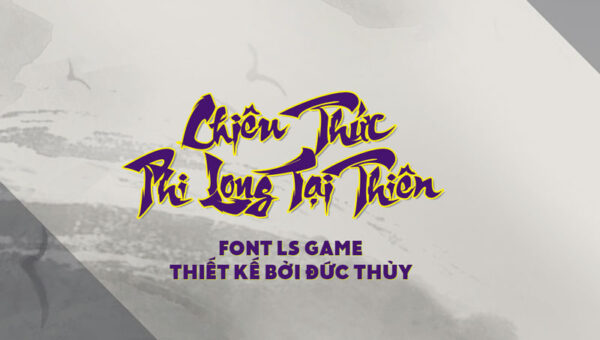
Font kiếm hiệp LS Game
Bộ font kiếm hiệp Ls Game phù hợp thiết kế content game thể loại game và các ấn phẩm bìa sách, quảng cáo, baner game…
• Font game kiếm hiệp này được thiết kế bởi Đức Thủy, Font lấy cảm hứng kho chơi game Võ lâm truyền kỳ.
• Font đặc biệt có nhiều ký tự thay thế khác nhau và được tối ưu để phù hợp trong nhiều trường hợp thiết kế.
• Các ký tự được thêm quy tắc gõ, hoặc insert vào table glyphs của từng chữ cái.
Bộ font kiếm hiệp Ls Game V1 phù hợp thiết kế content game thể loại game và các ấn phẩm bìa sách, quảng cáo, baner game…
Bộ font game kiếm hiệp này được thiết kế bởi Đức Thủy, Font lấy cảm hứng kho chơi game Võ lâm truyền kỳ.
Admin muốn tạo nên sự khác biệt trong các sản phẩm game, tăng giá trị cho việc PR game mới.
Font đặc biệt có nhiều ký tự thay thế khác nhau và được tối ưu để phù hợp trong nhiều trường hợp thiết kế.
Các ký tự được thêm quy tắc gõ, hoặc insert vào table glyphs của từng chữ cái.
Dưới đây là các hình ảnh demo có nội dung về chủ đề game kiếm hiệp, tam quốc mà admin thường chơi.
Bộ font chữ đẹp lsgame v1 được thiết kế bởi đức thủy, phù hợp thiêt kế content game thể loại kiếm hiệp, tiên hiệp và các ấn phẩm bìa sách
Bộ font chữ đẹp LsGame V1 được thiết kế bởi Đức Thủy, phù hợp thiêt kế content game thể loại kiếm hiệp, tiên hiệp và các ấn phẩm bìa sách